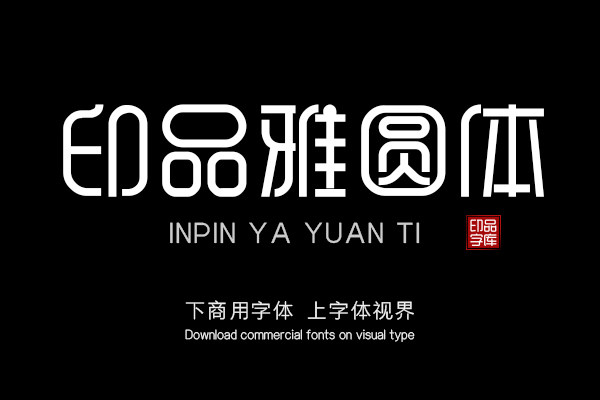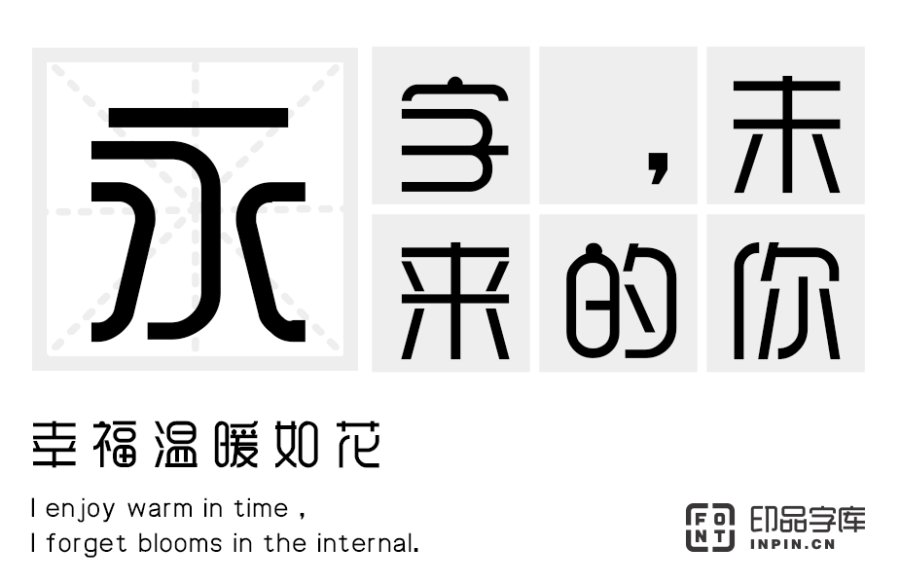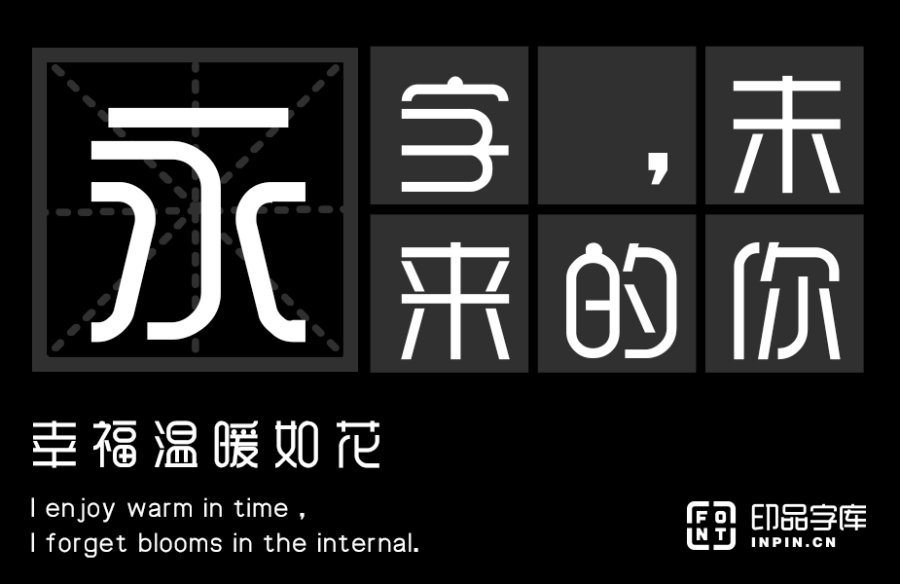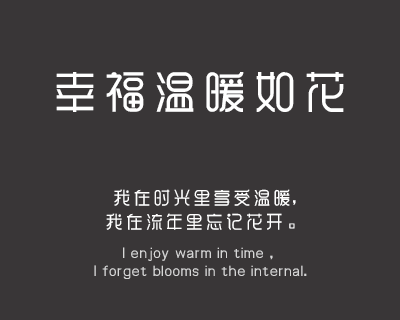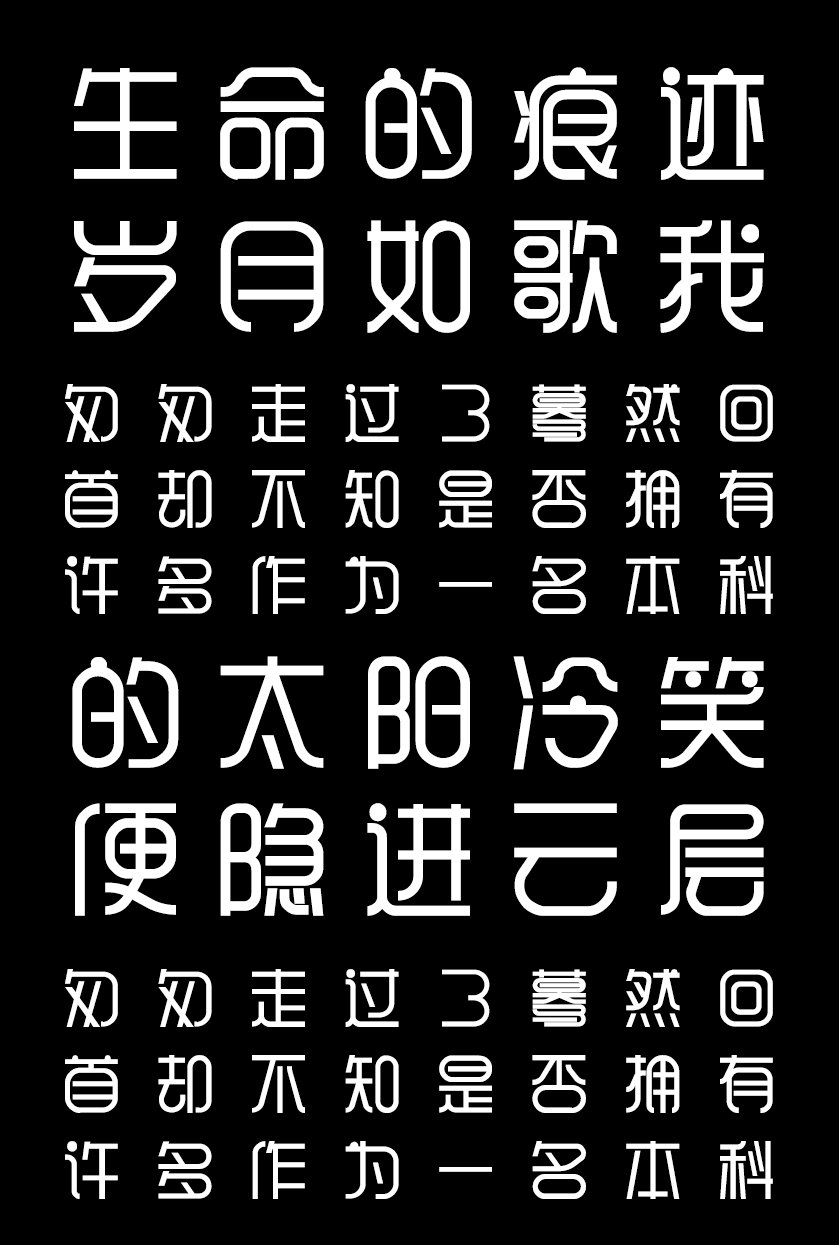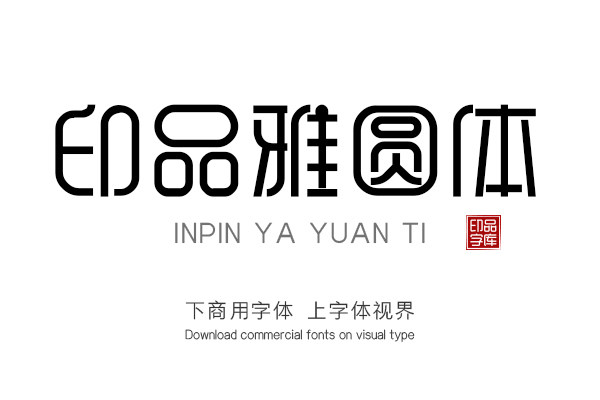
所谓圆体是英文书法的延伸及日常化,较为随意。雅圆体,对弧形做了内凹外凸的处理,使得笔画更加居中圆滑。表面结构匀称统一,字型做了细致比例的调整,整体观来更加珠圆玉润。加强装饰感的同时,多添了一分俏皮可爱。分享到
设计师通过对传统圆体的认真分析,线条的对比调试,字体空间的分配,色彩度的感应变化及字体视觉真实与假象的运用,最终设计出这款印品雅圆体。 印品雅圆体起笔于收笔处多了弧形外凸的处理方式,使得笔画更加饱满圆滑。笔画表面匀称统一实则密笔画处做了细致比例的调整,巧妙的运用了视觉欺骗原理,整体观来更加圆润协调。 印品雅圆体中宫外收内敛,重心向上微移;整个字更加精神。 印品雅圆体,结构上方正端庄接近黑体,但装饰感又多于黑体。笔画的处理是其灵魂,起始处珠圆玉润。整个字圆润饱满,整个字规整但又俏皮可爱。字与字之间独立而又联系,气息舒畅明朗。这款字可用于个性LOGO、广告、屏显、动漫、影视等场景中。